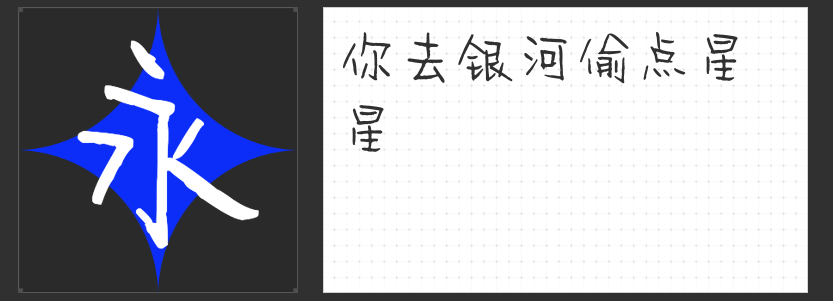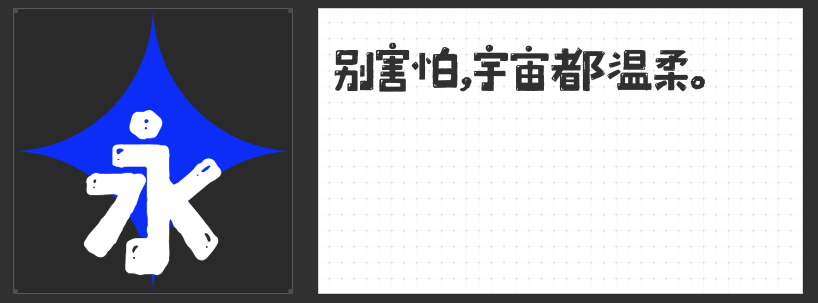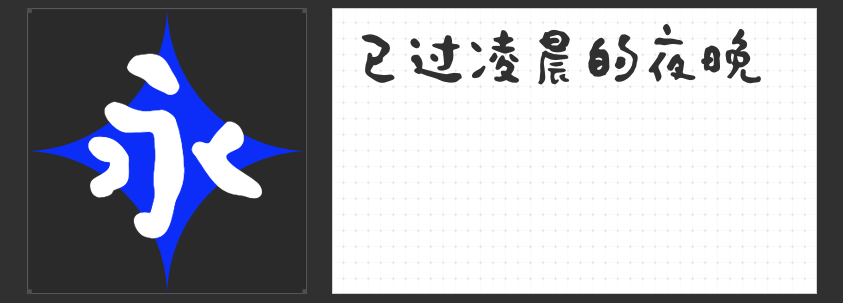
印刷设计中的艺术之选:四款独具匠心的字库字体推荐
在印刷设计的视觉叙事中,字体是承载情感与风格的核心载体。一款恰到好处的字体,不仅能提升版面美学价值,更能强化主题表达。以下四款字库字体,以独特的设计语言与工艺质感,为印刷品注入艺术灵魂。
一、喵字绘本体
专为绘本市场定制的喵字绘本体,以突破性的设计思维打破传统手写字体的局限。设计师将机械制图的精准线条与手绘笔触的灵动韵律巧妙融合,创造出兼具工业质感与人文温度的视觉语言。笔画转折处保留了手绘时的自然抖动,却在整体结构上遵循几何逻辑,形成独特的"可控性随机感"。这种矛盾美学使其在儿童绘本、艺术画册等印刷品中,既能营造童趣氛围,又不失设计专业性。
二、MyFont凌渡未卜简
作为一款为展示效果量身打造的手绘字体,凌渡未卜简以孩童涂鸦般的笔触构建视觉趣味。其笔画设计暗含黄金比例,在看似随意的形态中隐藏着严谨的结构逻辑。圆润的转折与适度的倾斜角度,既保留了手写字体的温度,又通过数字化处理优化了阅读体验。这款字体尤其适合用于需要营造轻松氛围的印刷品,如创意杂志、文化海报等。
三、字恋狂特别黑简
以强烈对比为设计核心的特别黑简,通过横竖笔画的戏剧性粗细变化,构建出极具冲击力的视觉效果。设计师刻意保留手写时的飞白痕迹与笔画边缘的毛糙质感,在工业化印刷中重现书法艺术的原始生命力。这种不规整的创意表达,使其成为艺术书籍、实验性印刷品的理想选择。
四、字恋狂深夜简繁
深夜简繁以水墨笔触为灵感源泉,通过数字化重构演绎出东方美学的现代诠释。蜿蜒曲折的笔画如同被夜色浸润的溪流,在纸面留下自然流动的痕迹。设计师巧妙控制字形的扭曲程度,既保持文字的可识别性,又营造出梦境般的迷离氛围。这款字体特别适合诗歌集、艺术摄影集等需要营造氛围感的印刷作品。
这四款字体通过不同的设计路径,展现了印刷字体的无限可能。它们或以矛盾美学突破常规,或以童真笔触唤醒情感,或以视觉张力震撼人心,或以诗意流动抚慰心灵,为印刷设计提供了丰富的表达维度。